编者按:不论是UI设计师还是网页设计师,每天都在同字体与文本打交道,可是我们真的了解文本/字体 对于界面的意义和功能么?Viljami Salminen 今天就来帮你刨根问底,从根子上开始帮我们普及UI界面中字体与文本的使用之道~
早在2004年,我刚刚开始职业生涯的时候,sIFR 还是一个特别火的概念。Shaun Inman 所创造出来的这项技术,通过Flash + JS + CSS联合实现在不替换页面中文本元素的情况下,对文本进行更为细腻准确的效果渲染。( 使用sIFR你可以任意定义WEB中的文本字体,即便是客户端浏览器未安装的字体。sIFR使用Flash渲染字体效果,可以平滑消除文本锯齿,你可以像使用用CSS控制文本一样轻松得到各种文本效果)而在当时,这项技术是在Firefox和Safari 这样的浏览器当中使用自定义字体的唯一途径。不过由于这项技术极为吃内存,让它在几年内很快过时了。而2007年所问世的iPhone 甚至直接同Flash 技术划清界限。说回文本和字体本身,作为界面中最重要也是最常见的元素,它本身也承载着样式、传递不同的信息,可以说是界面设计中的一个核心分支也不为过。
2008年,主流的浏览器最终还是选择了支持CSS3的@font-face 规则,这一规则在早期的CSS中也存在,但是在1998年的时候被剔除掉了。CSS3的这一改变令人振奋,我正好将这一技术运用到一个客户所托付的项目上来,使得网站的浏览体验得到了明显的增强。
也正是因为我入行初期对于字体和排版的热爱,使得我乐于钻研这些东西,愿意为了一丁点的强化和改变而进行深入的摸索。在今天的这篇文章当中,我希望将我所学到的这些基本的知识同大家分享一下,希望大家对于界面有着更加深入的认识。
最初的图形界面
文字和排版可以追溯到五千年前,而图形化界面仅仅只有40年的历史。最关键的转折点出现在1973年的施乐,最早的图形化界面出现在了他们的Alto电脑上,而这个设计就是现如今图形化界面设计的基础。在Alto 的界面诞生后的10年里,几乎是它一家独大,并且它也被大家视作为数字技术的未来。
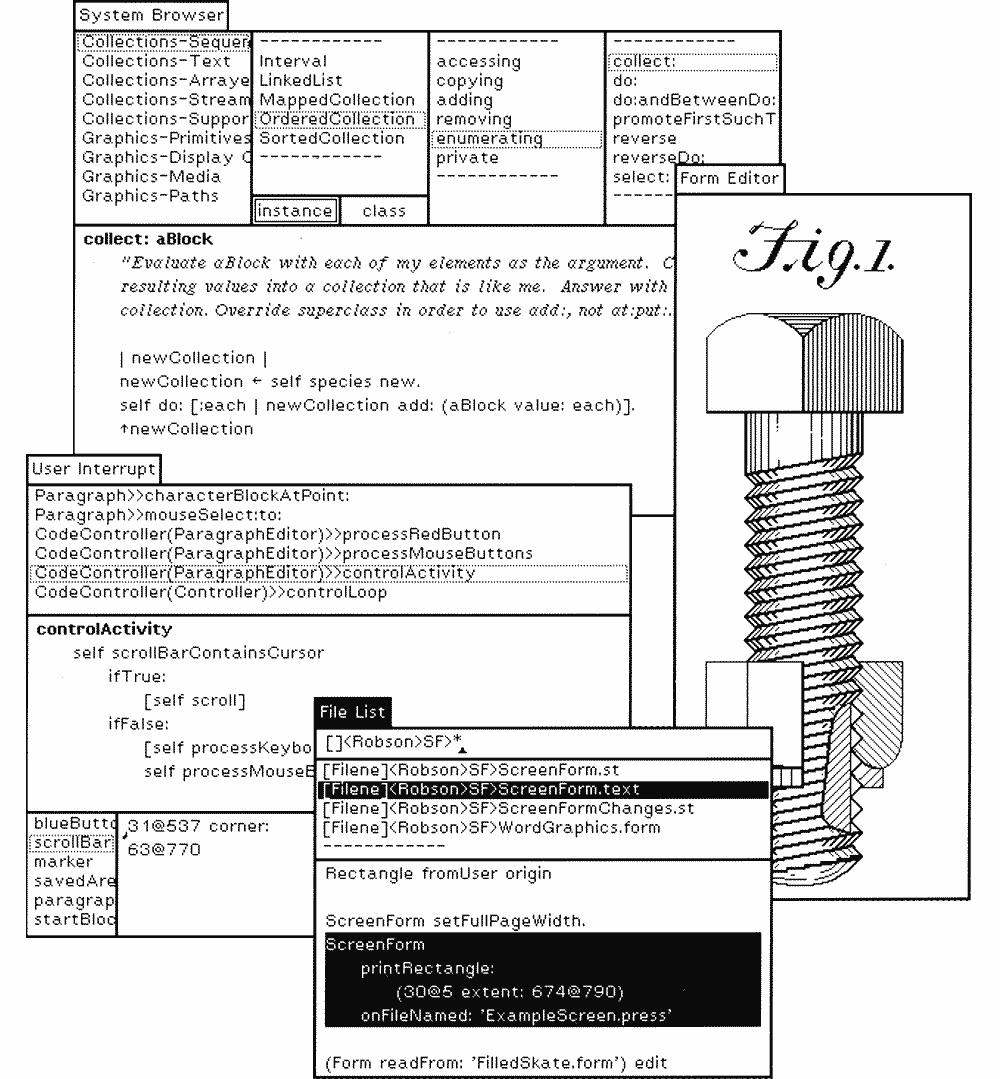
早期的Alto 在80年代进化为著名的施乐之星,而施乐的这个设计方案也成为了第一个商用的操作系统图形化界面。
不过不论是Alto 还是施乐之星,都没能真正意义上崛起。不过施乐的图形化界面最终深深的影响了苹果和微软的道路,比尔盖茨和乔布斯先后在施乐的研发中心观摩了施乐之星的运作,而乔布斯更是在1984年先人一步发布了著名的Macintosh 系统,也就是后来我们所熟知的Mac OS。
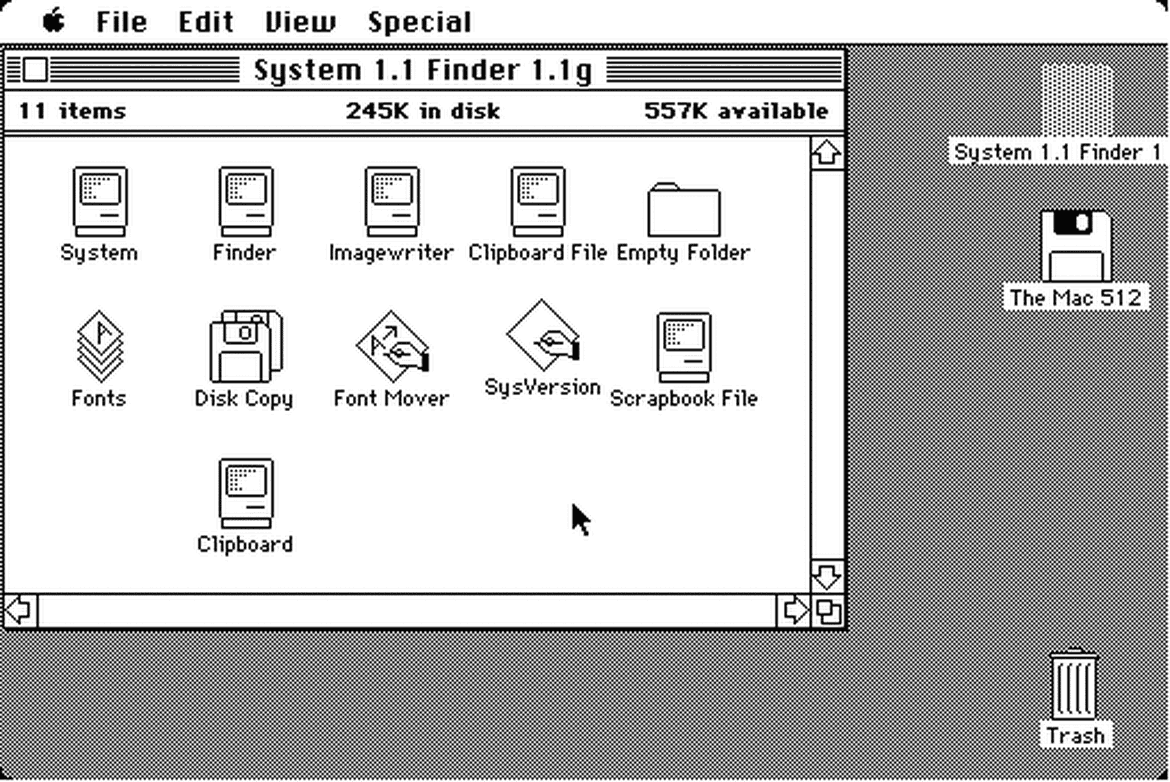
Macintosh 的发布不仅仅意味着相对成熟的GUI的出现,而且它为大众带来了真正意义上的自定义字体的功能。这款系统内置了许多以著名城市命名的字体,也正是在此之后才有越来越多的著名字体的数字版本在数字平台上发布并应用。
仔细观察这些早期的字体,我们能够发现,虽然已经是图形化的界面,但是其中绝大多数的界面元素都还是以纯文本的形式而存在,它们以一种奇妙的方式被整合到一个界面当中。循着界面的发展历程沿路看过来,不难发现,文本和排版几乎是贯穿始终的主线,它是一个不容忽视的核心类别。
文本即界面
界面中的每一个文字、每一个字符都很重要。好的文本是好的设计。文本是最根本的界面,是我们设计师来塑造和打磨这些信息。
看看下面的天气界面的设计,想象一下将所有界面元素都摆在桌上会是什么样的效果:无非就是两张图,几个图标和一大堆文本。
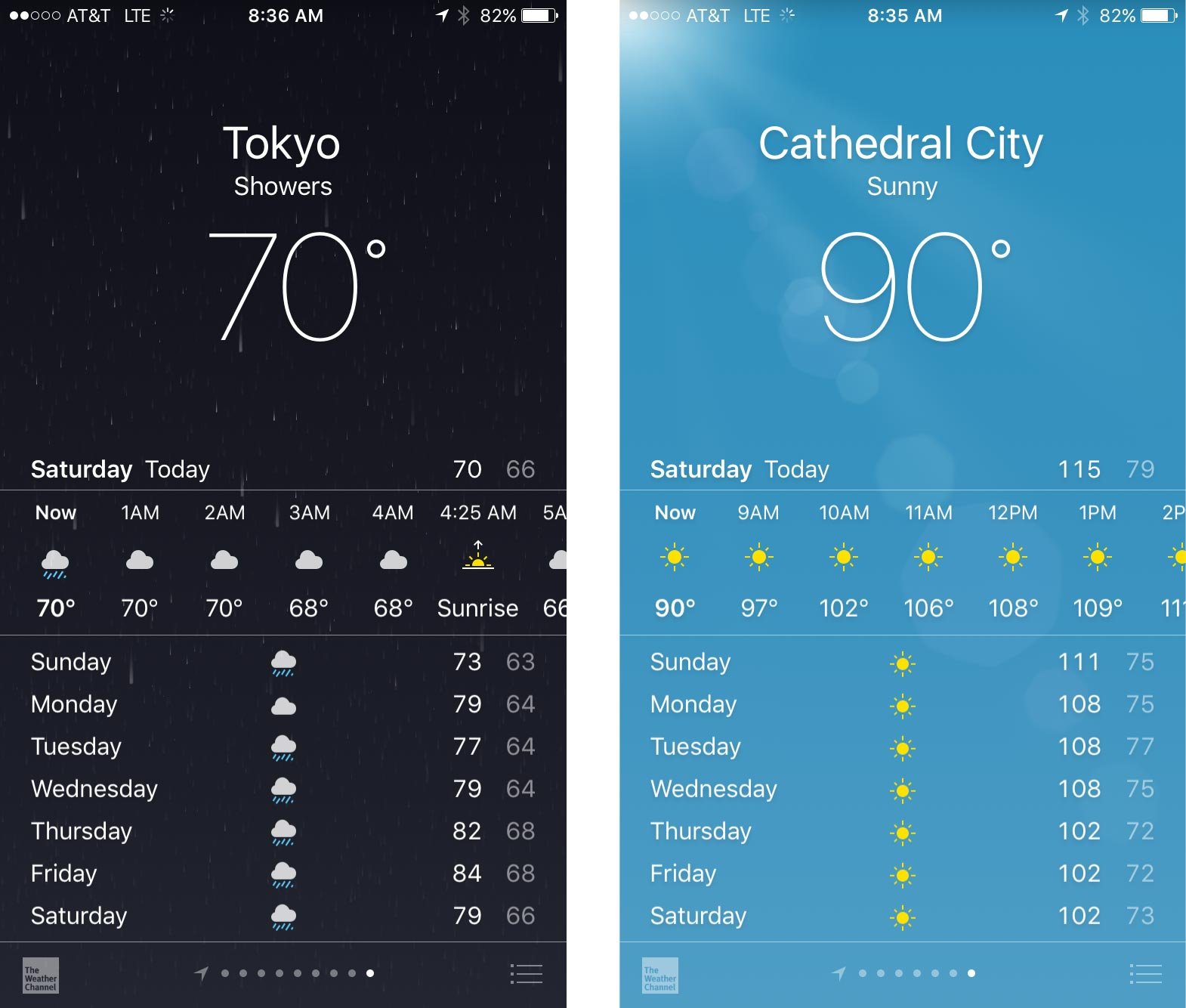
作为设计师,工作并不是将一堆随机的内容和元素排布在屏幕上,让它们看起来够漂亮就行了。真实的情况是,我们要从最核心的内容和文本开始着手,然后从这里着手细化,并完善出其他的部分。这就是我们工作的核心。
文本的清晰度同样扮演着关键性的角色。如果我们的大脑花费一两秒钟单纯只是分辨一个字形,那么清晰度上的微小差异是无伤大雅的。可是当它们组合成为大段的文本,不同的字母组合构成不同的词汇、段落的时候,清晰度的影响就更大了,排版的重要性也显得更加明显了。
当然,影响界面设计的文本属性还有很多,比如平衡性,定位和层次结构,但是好的文案和排版的影响至少占据整体影响的95%。
在伟大的设计师眼里,文本不仅承载内容,而且可以构成界面。
– Oliver Reichenstein
我们如何阅读
既然屏幕上的文本显示是如此的重要,那么我们应当先了解人们是如何阅读的,而文本显示又是如何影响我们设计决策的。
读过Billy Whited 的文章《Setting Type for User Interface》之后,让我对于文本阅读的效率有了更深的认知。一个少于20个字母的独立单词放在句子中会更快被理解,而单独放置的时候我们需要耗费更长的时间来识别。
其实这个研究结果也表明我们阅读较长句子的时候,并非是逐个单词地阅读,而是跳跃着阅读功能性的词汇,我们将这种阅读方式称为离散跳跃式阅读,俗称扫视。
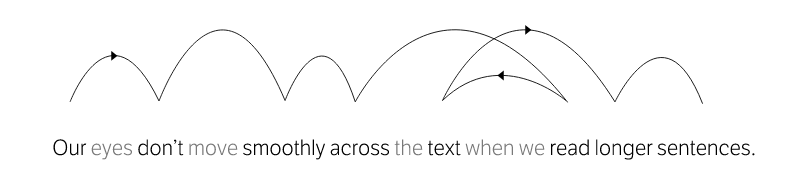
扫视让我们的阅读能力更强,我们甚至会跳过短的功能性词汇。
我们应当记住这一关键特征,因为我们的界面中所承载的词汇大多是孤立的单词。简单说来,界面是无法利用扫视这种方式来获取信息的。
总的来说,单词在阅读中发挥着无比重要的作用,无论是作为内容还是作为界面元素,均是如此。无疑,选择合适的字体就相当重要了。
过去,人们常常认为眼睛和大脑是通过单词的外轮廓(Bouma Shape)来识别单词,当然,后来的研究证明这个想法是错的,单词的可读性和易读性的影响因素不止是外轮廓,字母本身的形态、细节和清晰度同样深入的影响着它的识别度。
是什么让字母清晰可读?
其实这个问题一开始并不是那么好回答。阅读很大程度上依赖于我们的习惯,越常见的内容对我们而言越容易识别。这样一来,我们就不那么容易判断让字母清晰易读的影响因素了。为了了解这一点,我们需要将句子分割为单词,分解单词为字母,在字母中查看细节。
早在2008年,维多利亚大学心理学系根据测试结果得出结论,大写和小写的拉丁文字母是最容易识别的,也最易于阅读。
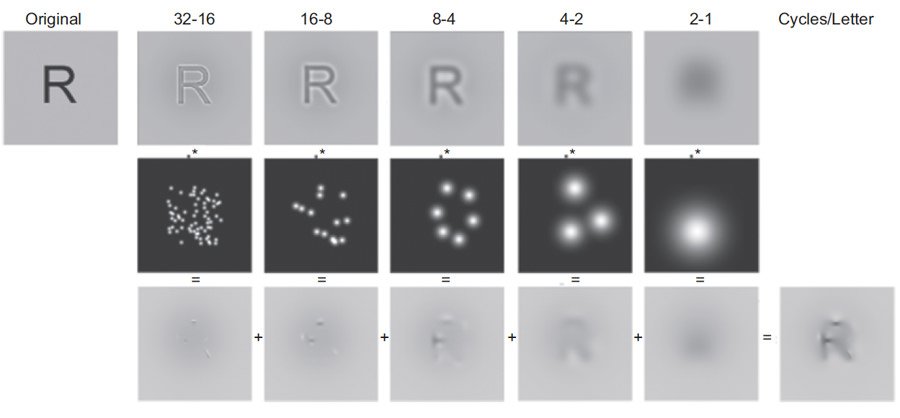
这项研究有趣的地方在于,它揭示了一个事实:每个字母延伸出来的线性端点是最易于识别的地方,也是每个字母的特点所在。
上面的图片标识出了这些最易于识别的部分。每一款字体在这些部分应当设计为最通用、最为人所熟悉的样式,同样的,它们也应该强调每个字母的差异。
在2010年的时候,另一项由 Sofie Beier 和 Kevin Larson 开启了一个新的研究项目,这项研究专注于测试经常被误读的字母和字符的识别度。
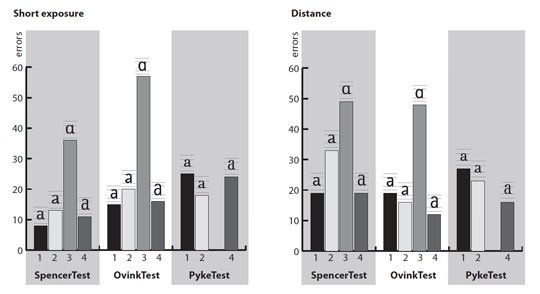
这项研究表明,在相同的字体和相同的尺寸、相同字重的情况下,有些字体或者变体的细节确实比其他的更加清晰、更易于识别。这项研究的结果说明,纤细的字体加粗之后识别度效果会明显会增强,而字母的X高度如果能够占据上伸区或者下探区的空间,识别度会更好。
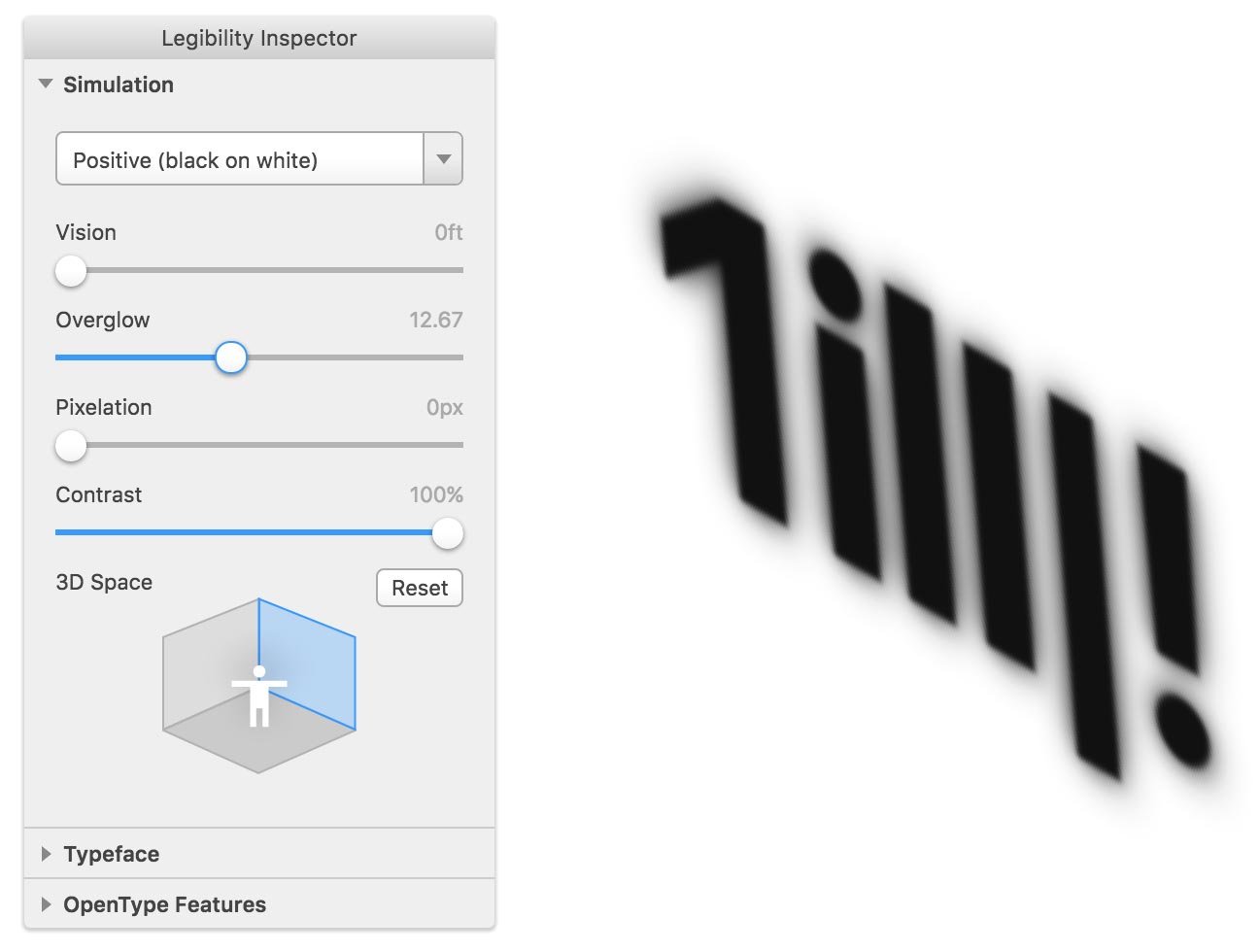
为了更好的理解字体的清晰度的概念,你可以下载我所开发的这款工具 Legibility APP 来测试不同字体在模糊、炫光等多种不同情况下的清晰度和辨识度。这是一款处于测试阶段的工具,可以在Chrmoe、Opera和Safari 中运行。
UI中的字体使用
理解了用户阅读的方式和字体可读性的影响因素之后,我们应当开始了解UI中的字体的几个关键因素。下面是UI中字体使用的10个关键因素。
1、可读性
可读性是UI中字体所需考虑的首要因素。字母字形必须清晰可辨,作为UI元素,其中不同的字母必须可以被用户轻松辨别出差异。许多经典的字体,甚至包括 Helvetica ,都没办法清晰分辨 字母 i 的大写形态 I,和大写字母 L的小写形态 l,这在界面设计中无疑是有影响的。
上图中,左边的字体为 Source Sans Pro , 右边为 Helvetica,无疑对于 Illiterate 这个词Helvetica 字体下前三个字母完全无法分辨。有部分用户也同意Helvetica 并不适合作为UI界面的显示字体而存在,因为这款字体终究是为平面印刷显示而设计的,并非为屏幕而生。
在iOS 7 时代,苹果短暂地将 Helvetica 作为系统的主要显示字体的时候,曾对特定的用户群体造成过信息识别的困扰。这也最终催生了我们现在所看到的苹果官方字体 San Francisco。旧金山是为UI界面而生的字体,它的x高度比Helvetica 更高,字母间距更宽,字母间的识别度更高。
2、适度
一款理想的UI界面所用的字体,不应当过于“显眼”,而该是悄无声息,“隐型”的。当用户在试图完成某项任务的时候,字体不应当给用户以“出戏”或者“显眼”的感觉,也就是说,字体不应当超出用户的认知负荷,而内容和信息才应该成为真正的关注点。
3、灵活
给UI界面使用的字体应当具有灵活性。我们曾经为 Medium 做过用户体验设计,作为一个网页博客平台,我们很难去控制用户的能力、内容、浏览器、屏幕尺寸、网络带宽和连接速度,包括输入法。
所以我们最终为它所选取的字体应当支持大量不同的内容,在不同的尺寸下拥有良好的识别度,能够兼容不同的设备,尤其是在小屏幕上。Sans serifs 字体就是专门为小尺寸低分辨率屏幕而定制的。
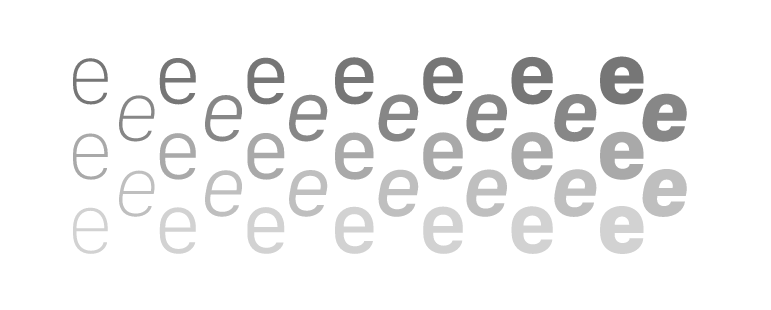
4、x高度的上限
x高度的参考标准是小写字母x的高度,同等尺寸下,x高度更大的字体更易于识别。不过x高度也不是越大越好,当x高度超过一定限度的时候,小写字母n和小写字母h就很难分辨了,这一点应当注意。
5、更大宽高比
字母的宽度和高度的比例也是相当重要的一个属性。宽度和高度比例越高,字母在小屏幕上的识别度就越高。
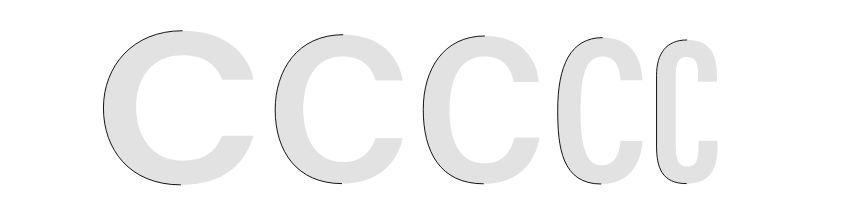
6、宽松的字间距
字母之间的间距和字母内部的空间同样是影响字母可读的因素。字母间距太小同样会影响整体的可读性,而好的显示字体会更好的控制字母间距,确保单词在视觉上的“透气性”,甚至可以营造出一种韵律感。
不过字间距不是越宽松越好,太过宽松会让整个单词看起来过于松散。有一个值得参考的标准,就是字母之间的间距应当比字母内的开口缝隙略小一点。
7、低笔触对比度
许多字体不同的笔画粗细不同,而对于UI界面而言,笔触间的对比度越小识别度越好。较大的笔触对比度下,字体在小尺寸屏幕上,较细的笔画会难于分辨。
8、OpenType 功能
OpenType 功能对于字体而言是相当重要的。支持OpenType的字体拥有更大的灵活性,对于不同的语言和特殊的字符有着更为优良的兼容性。
9、备用字体
接下来要说的情况可能大家多少都碰到过。网页在完全加载出来之前,部分内容因为字体没有加载而无法显示。
其实这可以通过先加载本地字体,显示内容,等网页字体加载好了之后再行替换,以达到无阻塞显示。这种方法的缺陷是需要预先设定一个可调用的本地备用字体。
10、Hinting
Hinting 指的是为了字体为了保证最大的可读性而针对显示器状况进行调整的过程。Hinting 可以通过匹配显示器的像素栅格让字体显示更加清晰,降低误读的可能性。
这项技术最初是由苹果公司所提出的,不过因为TrueType 字体技术的出现,Hinting 正在消失。
未来
随着新的UI标准、排版技术的提升,字体技术也在不断的进步,在不远的未来,字体会从传感器获得信息,更好的兼容不同的环境、随着亮度、设备、距离而进行智能化的调整,甚至复杂而庞大的中文字体,也可能作为灵活的网页字体而存在。
字体会让我们的工作更加便捷
让界面交互更快,更加触手可及
让UI更加易用
更加便捷
也更加清晰而高效